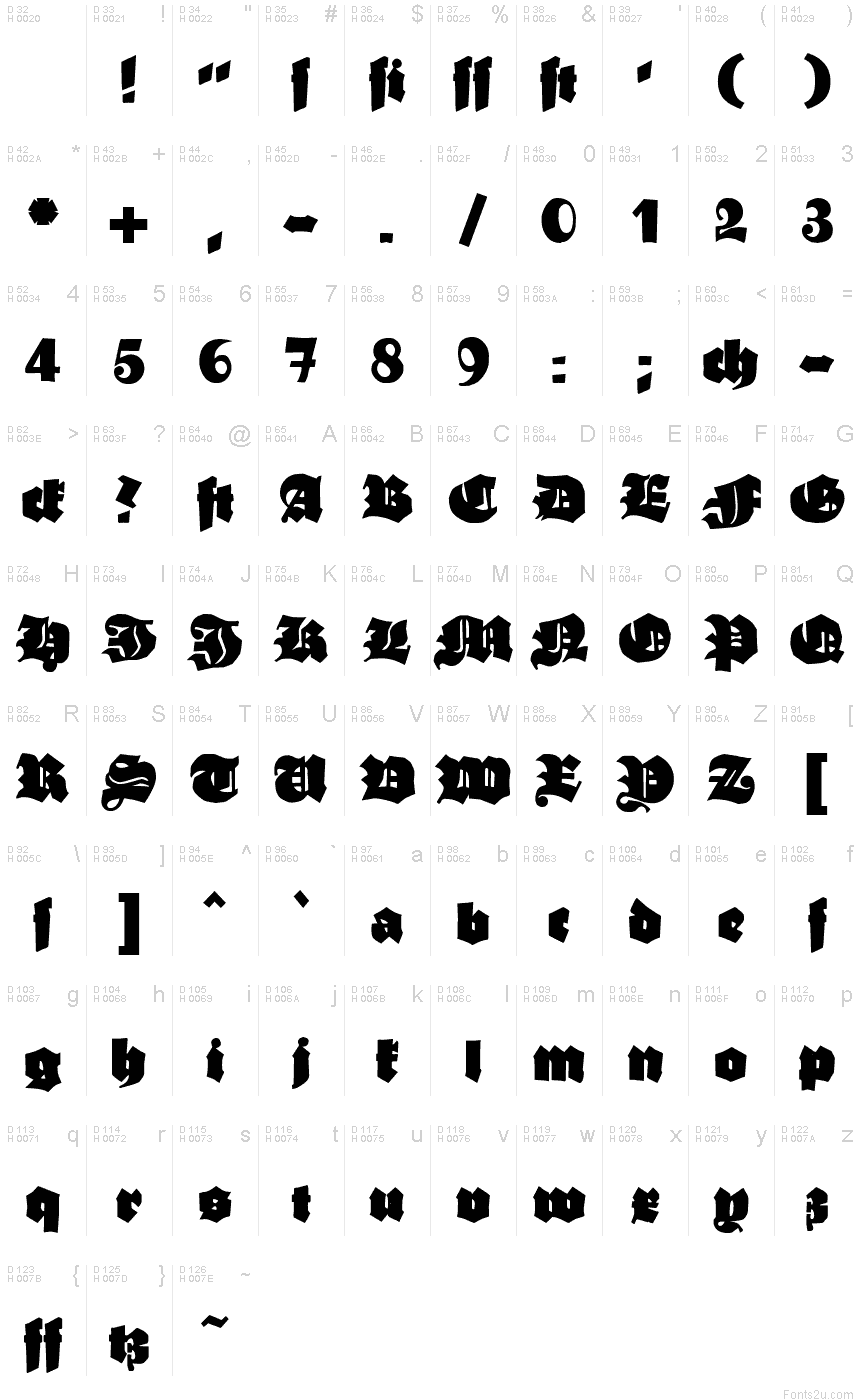
Ganz Grobe Gotisch
Ganz Grobe Gotisch od Typographer Mediengestaltung to darmowy, średniowieczny krój gotycki, który uderza niczym kleks czarnego tuszu na pergaminie. Masywne, blokowe pociągnięcia oraz ciasne, poszarpane krzywizny nadają mu brutalny, ręcznie ciosany charakter – bardziej przypominający mur fortecy niż delikatną kaligrafię. Litery ścieśniają się, tworząc gęstą, ciemną fakturę, która natychmiast przywodzi na myśl dawne sztandary, mroczne opowieści i ciężką muzykę.
Dzięki Ganz Grobe Gotisch Twoje nagłówki nie szepczą o „dawnych czasach” – one ryczą. Krój ten świetnie sprawdza się w logotypach zespołów metalowych, na okładkach książek fantasy, w tytułach gier, etykietach piw rzemieślniczych, plakatach oraz w brandingu eventów horrorowych, gdzie liczy się ciężar i groza. Połącz ten darmowy font z prostym, nowoczesnym krojem bezszeryfowym w przypadku mniejszych tekstów, a Ganz Grobe Gotisch pozostaw jako główny element logotypu lub nagłówka w dużym rozmiarze.